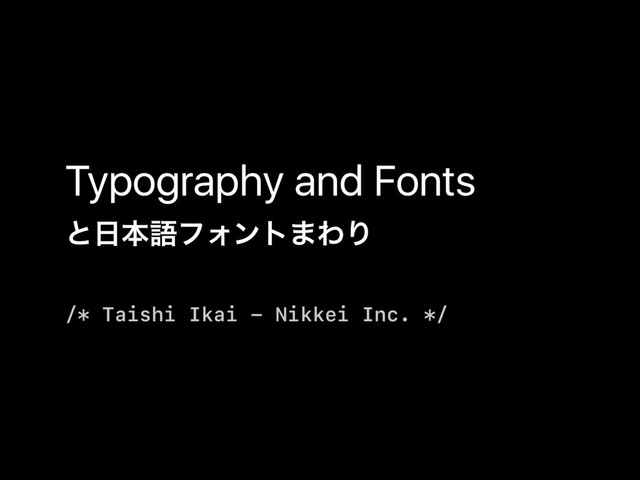
Typography and Fonts と日本語フォントまわり
Typography and Fonts /* Taishi Ikai - Nikkei Inc. */
ͱຊޠϑΥϯτ·ΘΓ
SF Mono
Xcode 8 ͷσϑΥϧτઃఆʹ
Source Han Code JP
Source Han Code JP github.com/adobe-fonts/source-han-code-jp
ABCDE NOPQR abcde nopqr 12345 શͯͷΣΠτɺάϥϑ͕෯ খ͍͞αΠζͰͷՄಡੑ ϥςϯɺΩϦϧɺΪϦγΞจࣈ
wmWMÆŒTM©%‰ Light wmWMÆŒTM©%‰ Regular wmWMÆŒTM©%‰ Medium wmWMÆŒTM©%‰ Semi Bold wmWMÆŒTM©%‰
Bold wmWMÆŒTM©%‰ Heavy શͯͷΣΠτɺάϥϑ͕෯
খ͍͞αΠζͰͷՄಡੑ . : • { * 0 . : •
{ * 0
খ͍͞αΠζͰͷՄಡੑ
Xcode 8 ͷσϑΥϧτઃఆʹ
San Francisco Fonts https://developer.apple.com/fonts/
SF UI Display SF UI Text SF Compact Display SF
Compact Text
Ultra light ― Black શ 9 ΣΠτ
SF UI Display SF UI Text SF Compact Display SF
Compact Text
SF UI Display SF UI Text SF Compact Display SF
Compact Text macOS iOS tvOS
SF UI Display SF UI Text SF Compact Display SF
Compact Text watchOS
SF UI Display SF UI Text SF Compact Display SF
Compact Text
SF UI Display SF UI Text SF Compact Display SF
Compact Text ϑΥϯταΠζʹΑΓɺࣗಈͰ Display ͔ Text ͕બ͞ΕΔ
τϥοΩϯά WANTEDLY จࣈͷִؒʢҰʣ
WANTEDLY τϥοΩϯά τϥοΩϯά͕ จࣈαΠζ͝ͱʹࣗಈௐ͞ΕΔ
มߋ
ʙ iOS 9
iOS 9 iOS 10
BLACK CIRCLE U+25CF
ʙ iOS 9
্ւɺࢦ࠾༻ݟૹΓͰ্ॏ͘ ʮཪޱ্ʯن੍ڧԽॏՙ
্ւɺࢦ࠾༻ݟૹΓ ʮཪޱ্ʯن੍ڧԽॏՙ
্ւɺࢦ࠾༻ݟૹΓ ʮཪޱ্ʯن੍ڧԽॏՙ ʮ
ߦ಄Ґஔௐ ্ւɺࢦ࠾༻ݟૹΓͰ্ॏ͘ ʮཪޱ্ʯن੍ڧԽॏՙ ňཪޱ
ຊൃ໌ৼڵڠɺʮൃ໌ͱԻָ…
࿈ଓ͢Δ ຊൃ໌ৼڵڠɺʮൃ໌ͱԻָ… ɺʮൃ ڠ
ຊൃ໌ৼڵڠŊ ňൃ໌ͱԻָ… ɺ ňൃ ڠ ࿈ଓ͢Δ
ӳࠃͷԤभ࿈߹ &6 ͕ܾ· Γɺੈքͷۚ༥ࢢͰυϧෆ͕
ӳࠃͷԤभ࿈߹ &6 ͕ܾ· Γɺੈքͷۚ༥ࢢͰυϧෆ͕ ۟ಡ͕ߦ಄ʹདྷΕͳ͍ͷͰɺ Ήͳ͘վߦ͕ߦΘΕΔ
ӳࠃͷԤभ࿈߹ &6 ͕ܾ· Γɺੈքͷۚ༥ࢢͰυϧෆ͕
ӳࠃͷԤभ࿈߹ &6 ͕ܾ·Γɺ ੈքͷۚ༥ࢢͰυϧෆ͕ڧ· ͍ग़͠
Typography and Fonts /* Taishi Ikai - Nikkei Inc. */
ͱຊޠϑΥϯτ·ΘΓ